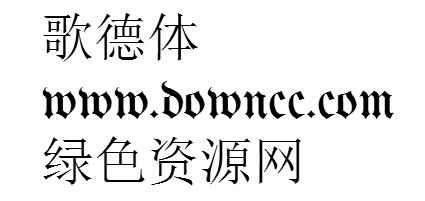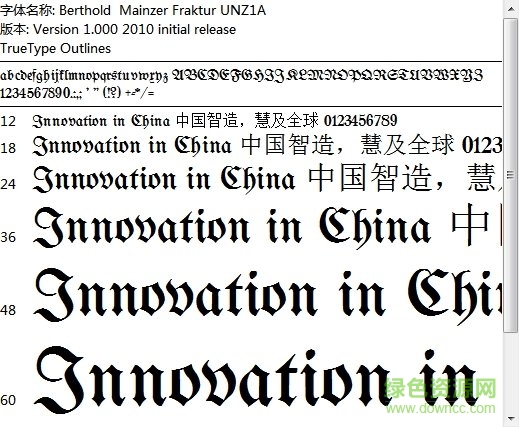
歌德體也譯作哥特使我們常見的字跡清秀的英文字體,每個(gè)字母均有著不同的書寫風(fēng)格,打破你對(duì)傳統(tǒng)字母的認(rèn)識(shí),感興趣的朋友就來綠色資源網(wǎng)體驗(yàn)吧!
本站為大家?guī)淼母璧嘛L(fēng)格字體為Bertholdr-Mainzer系列的兩款,歌德體是數(shù)理邏輯公式中常用的字母。
歌德體中形狀相似的有幾對(duì),包括A與U,B與V,D與O,I與J;
大量使用的文本很難閱讀,幸好在數(shù)學(xué)中用到的不多,在數(shù)理邏輯常用的就是ABC,有時(shí)還用M。
歌德體字體即哥特字體,是一款使用較為廣泛的特色書法字體,中文較為常態(tài),英文上卻有很大的變動(dòng),偏向于北歐風(fēng)格,給你的藝術(shù)設(shè)計(jì)、平面設(shè)計(jì)、包裝設(shè)計(jì)等帶來獨(dú)特美感!